OPPO R15的那种字体是如何制作的?
这段时间收到了很多童鞋问这个问题:
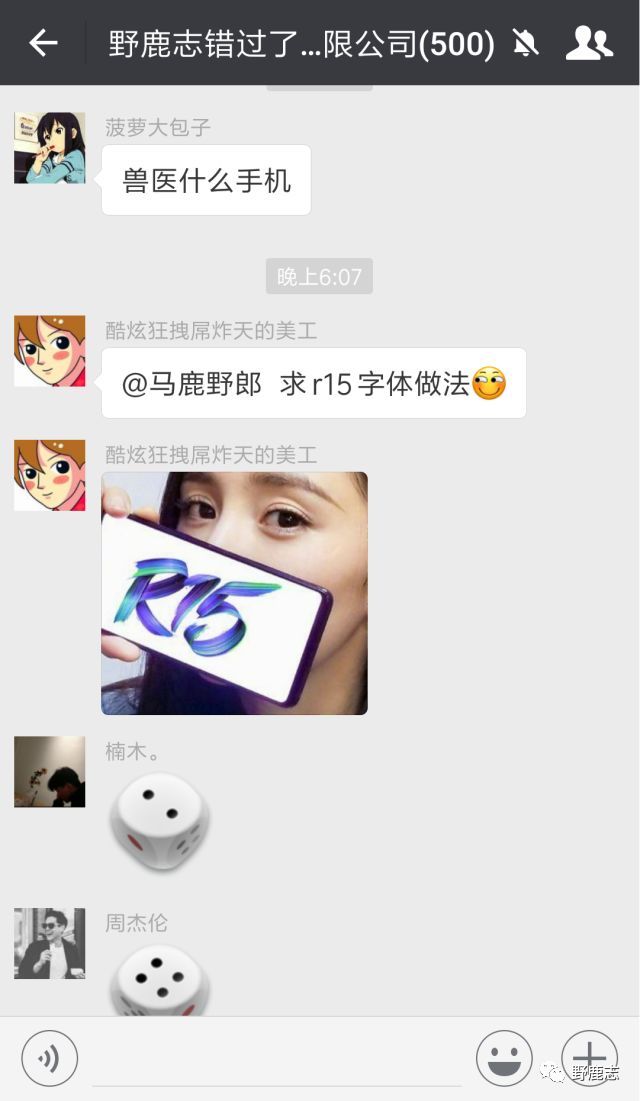
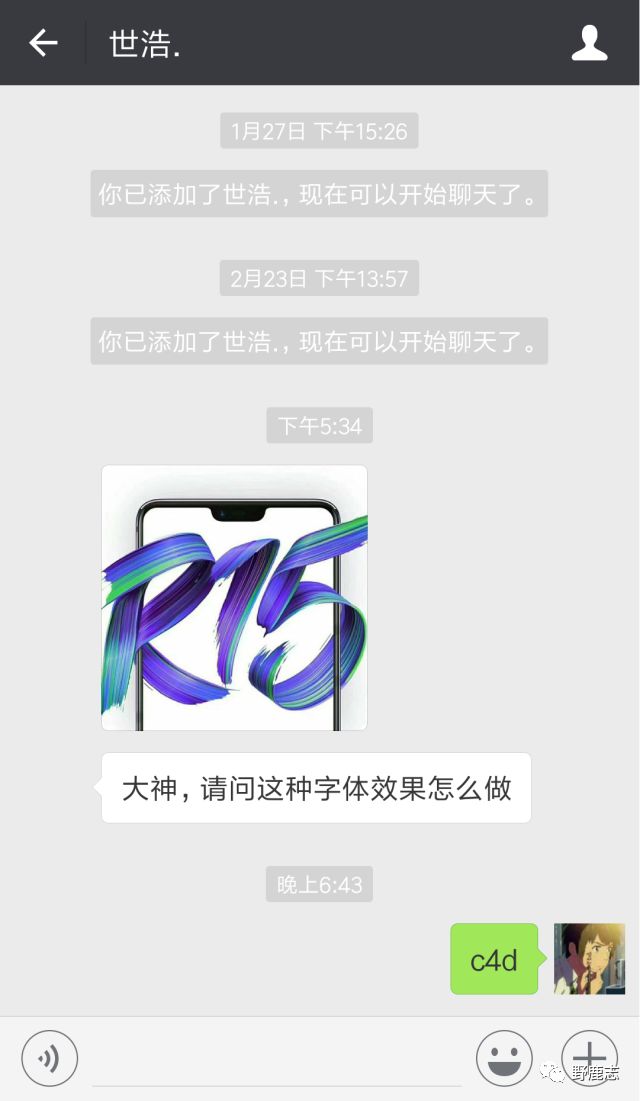
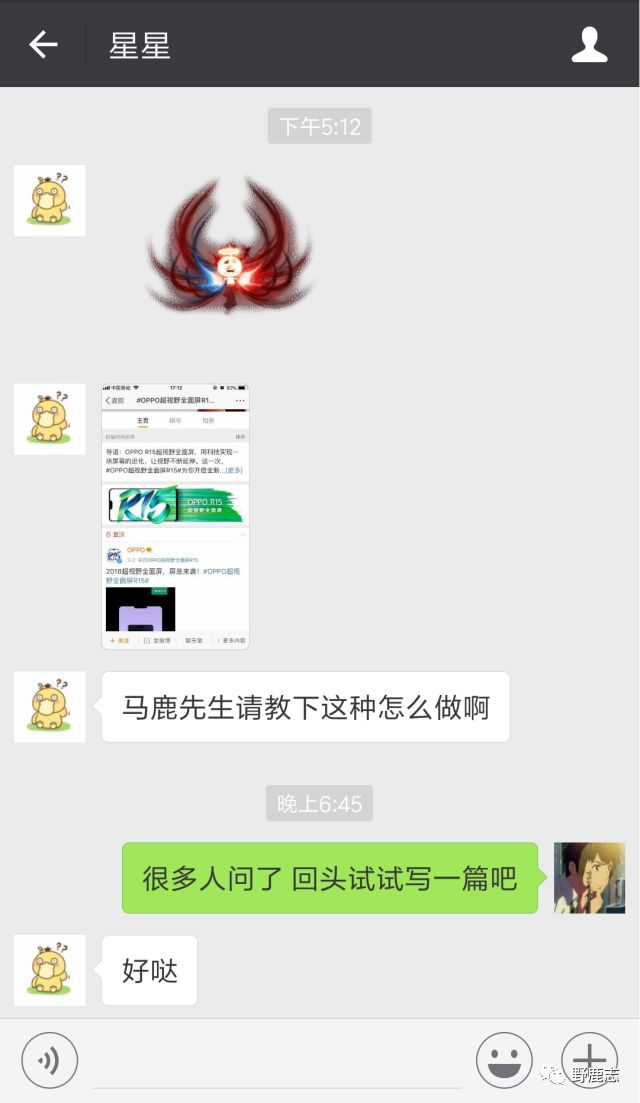
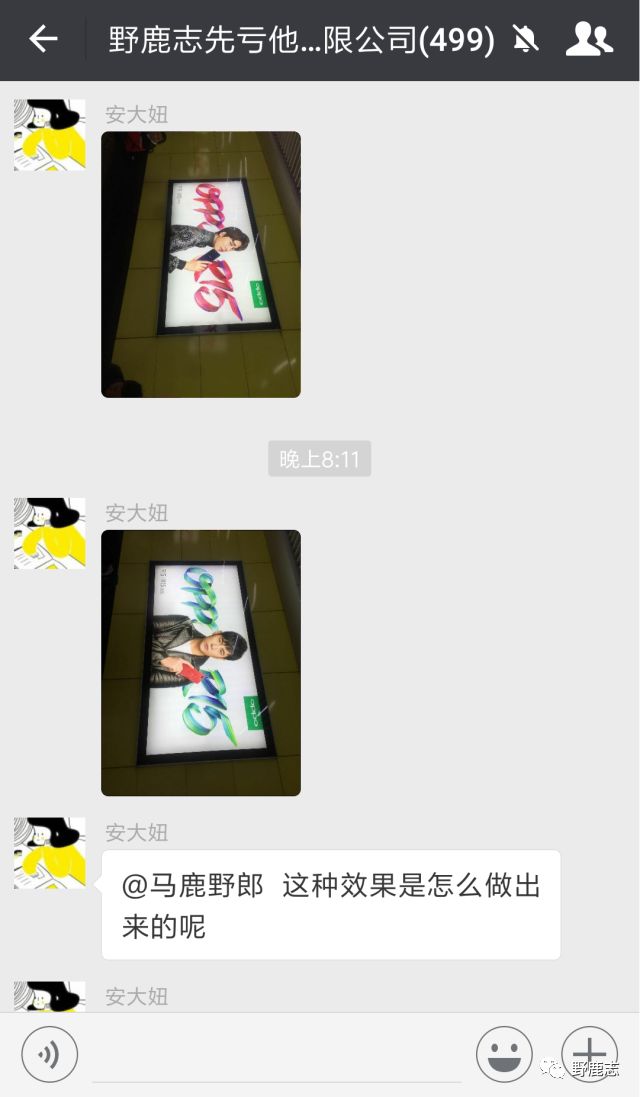
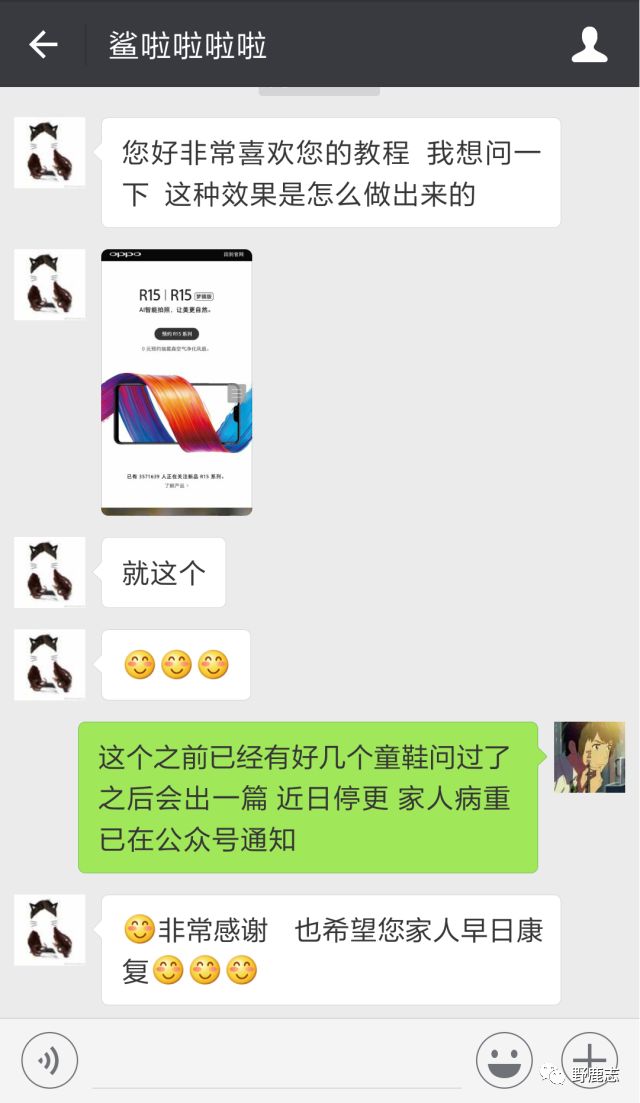
oppo R15的这个油漆文字的效果和最后这位童鞋的纹理效果其实都是用C4D的样条约束制作的,只是后期会用PS做一下润色。
今天我们就来分享一下这种oppo R15的油漆文字制作方法吧!
开始之前先借用最后这位童鞋问的纹理效果做一个小案例,来对样条约束这个好玩的工具进行一下简单的介绍吧。
打开C4D先在几何工具组里新建一个地形,同时改变一下Y轴的数值:
在样条工具组里新建一个样条,我这里选择的是蔓叶类曲线,同时改变一下它的类型以及宽度:
然后再在变形器工具组里新建样条约束:
这里有一点需要注意的是因为山峰是在Y轴方向变化的,所以记得把样条约束的轴向也改为Y轴:
由于样条约束是紫色的,所以根据我们以前的分享,需要让它成为地形的子集:
再把样条拖到样条约束对象属性栏的箭头所指位置,我们就可以看到对象已经发生了明显的改变:
参数这里同样我建议大家动手去尝试才能明白它们的具体含义。
我这里只说明一下,红色方框处的参数最大值均可以超过100,并且除了强度以外,其他三项的数值可以为负数:
尺寸这里我们可以通过曲线来改变对象不同位置的大小,按住CTRL键鼠标单击可以在曲线上加点:
旋转这里的操作方法和尺寸一样,区别是用来旋转对象的不同位置:
接下来你只需要调整样条约束的其他参数:
以及地形的各方面参数,看着效果调就好。如果你的样条是自己画的,也可以调整样条例的参数如锚点的位置。
由于我这里只是通过这个小案例去介绍工具,就不弄那么麻烦啦:
如果你想要纹理更加不那么尖锐,还可以添加一个细分曲面。
当然增加了细分曲面,会比较卡:
通过这个小案例,我们可以明白样条约束的作用:让几何体按照样条的路径进行形态的改变,同时保留几何体的纹理。
这一点和我们以前分享过的扫描有点相似,区别是扫描是让样条按照路径扫描出形态,并且不会有像样条约束一样能够保留几何体的纹理。
工具的作用介绍完我们开始今天的正题制作oppo R15油漆效果文字吧。
开始之前需要做一些准备工作,你可以去找一些油漆的素材。
由于野郎本来是有一些Ai的油漆笔刷的,就懒得去找了,这些笔刷我也会分享给大家:
如果你想改变笔刷的颜色也可以,选择自己想要的笔刷,用画笔工具画出来,再点击红色箭头处的重新着色图稿:
点击编辑,把颜色的锁链勾上,修改就行了:
我这里就不改变颜色了,直接把它导出为png图片:
由于我个人确实不太习惯C4D的钢笔工具,所以额外的用Ai做了一个文字S的路径,并且把它保存为Ai 8,一会儿导进C4d里:
准备工作做好了以后,打开C4d,执行文件-合并对象:
导入用Ai做好的路径:
新建一个平面,朝向改为Z轴:
新建样条约束,按照我们之前介绍的使用方法,让它成为平面的子集,并把样条拖到箭头所示的位置:
然后改变平面的相应的参数以及分段,让它看起来更平滑:
新建材质球,先赋予对象:
双击材质球,颜色通道的纹理的地方点击红色方框处载入刚才做好的颜料素材图:
这里选择不创建副本就行:
勾选Alpha通道,同样载入png图:
反射通道里适当的更改一下数值,看着材质球调就好:
置换通道里也载入素材,让它带有凹凸的感觉,参数看着办就好:
接下来再略微改变一下样条约束里的参数,我觉得就可以了:
可以再做这样的一个小球做点缀,材质的参数大家看着办就好:
接下来就是打灯了,大家都知道我还不太会打灯,所以这里也就不说我是怎么打的了,大家看着感觉来吧:
渲染设置中,输出里更改尺寸大小,保存里记得勾选Alpha通道,然后抗锯齿里勾选最佳:
渲染出图保存为Png格式:
接下来就是在Ps里操作啦,先画出类似这样的形状:
把字母和球分别摆放到合适的位置,这一步不用多说吧:
用深色椭圆,高斯模糊以后做投影,这一步也不用多说吧:
再搞一个投影装饰:
根据自己的喜好调一下色吧:
最后简单的排版导出图片看看效果吧:
大概就这样吧,我尝试过用Ai的3D贴图来做,但是太卡了,不如用C4D来搞。